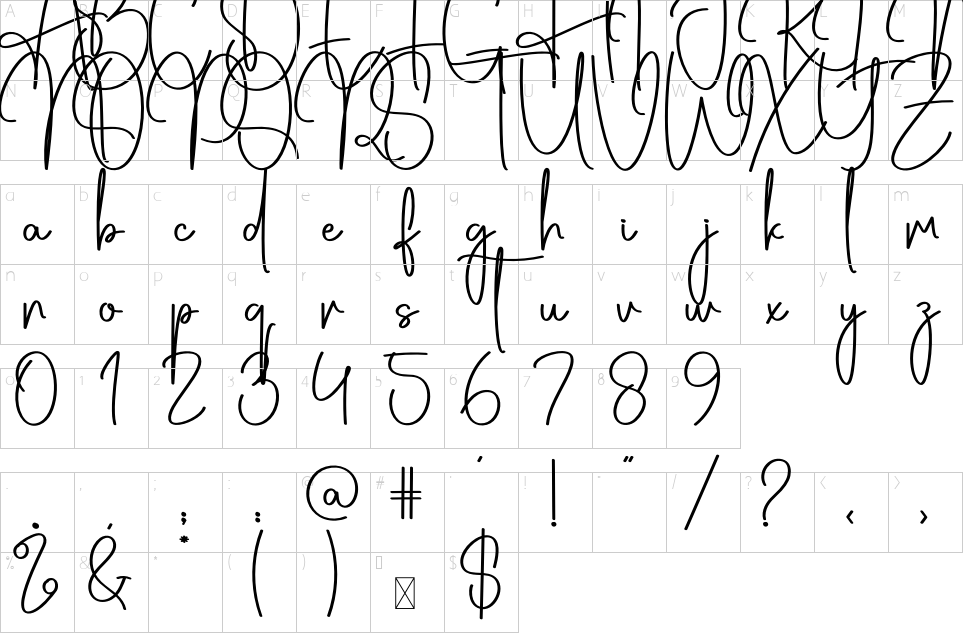
A fonte Auntybaby oferece um toque de descontração e personalidade, uma escolha ideal para aqueles que buscam uma fonte divertida para trabalhos e projetos pessoais. Desenvolvida por scratchones, esta fonte foi projetada para permitir que você personalize seu design de maneiras únicas e divertidas, seja para criar um site pessoal, personalizar documentos ou produzir uma aplicação. Com seu design original e caracterizado, a fonte Auntybaby já foi baixada 510 vezes, uma indicação de seu grande potencial e popularidade. Ideal para quem procura um visual alegre e único, Auntybaby é uma fonte que você certamente vai querer ter em seu arsenal de recursos gráficos.